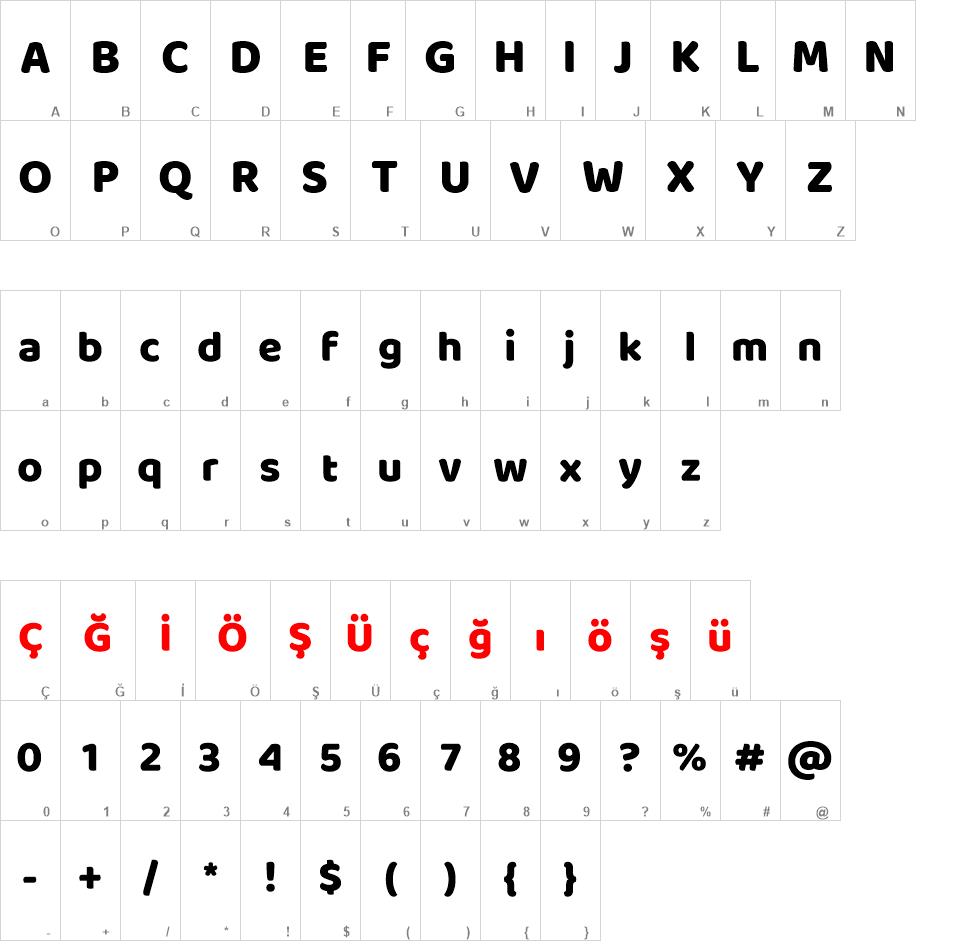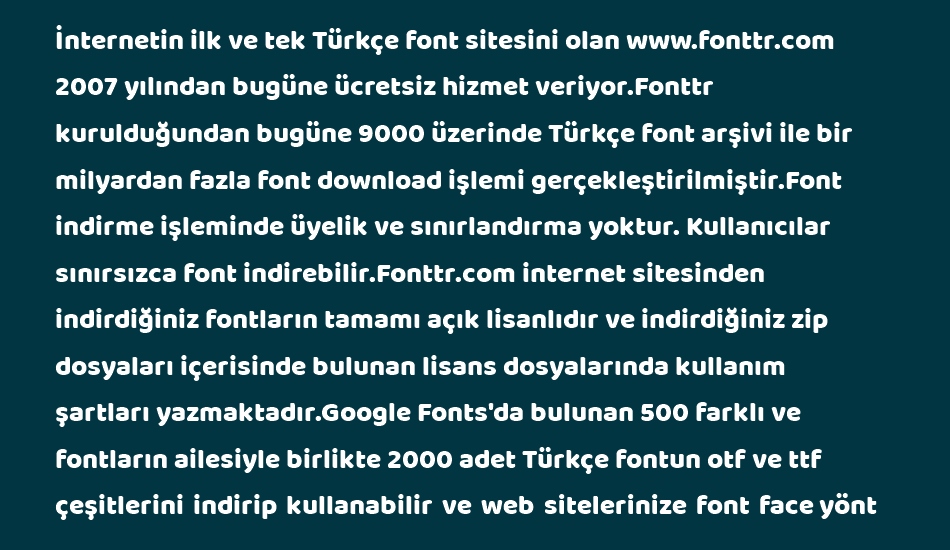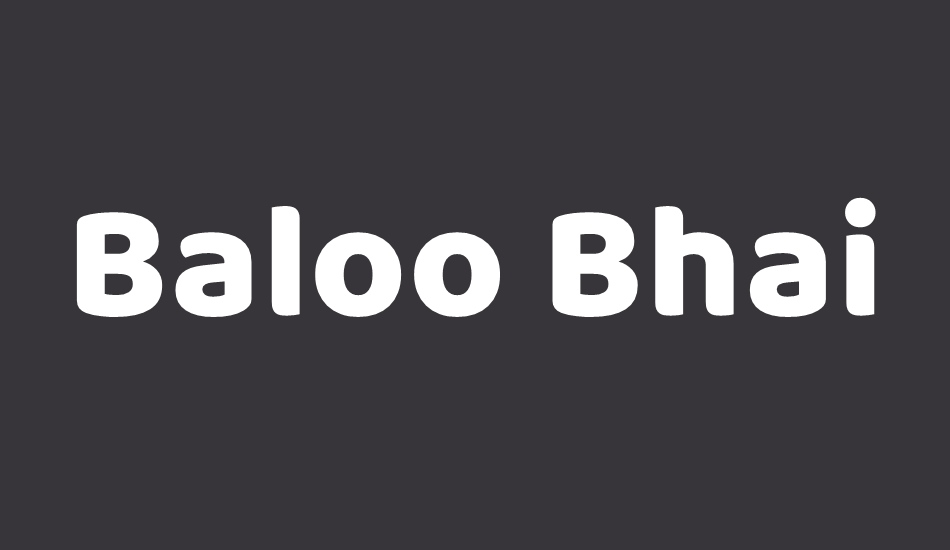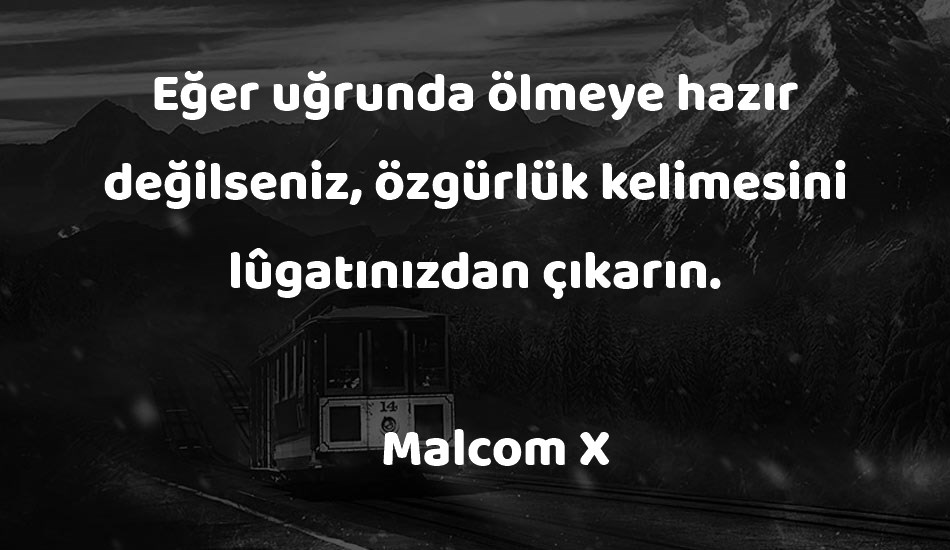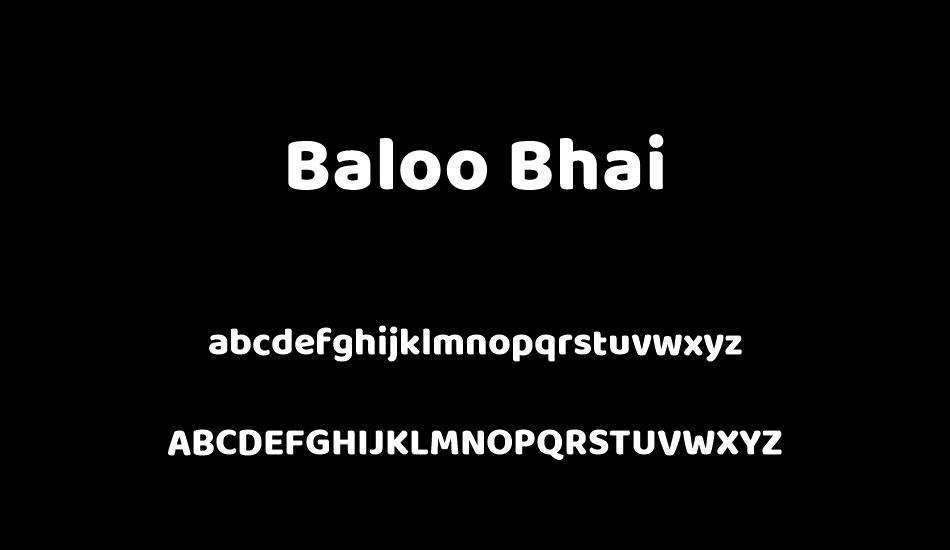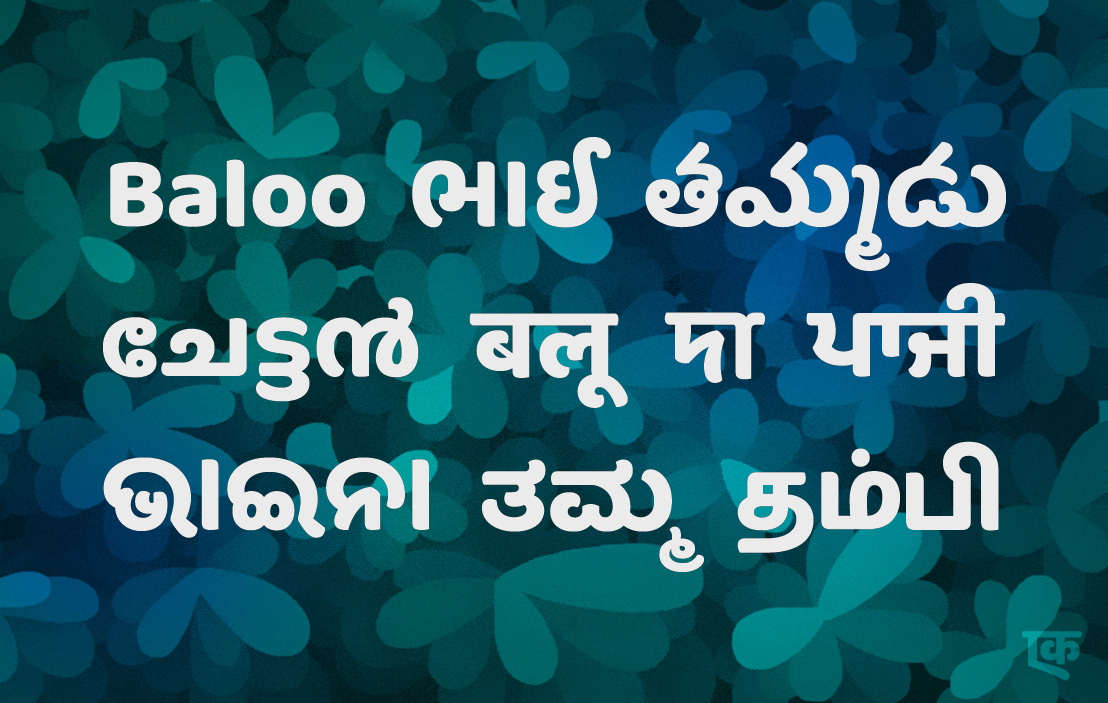
Baloo font
Bir kürk katında sivri pençelerin mükemmel bir karışımı olan Baloo, Ek Type'ın kullanışlı bir ekran yazı biçimidir. Dokuz Hintli senaryonun yanı sıra Latin muadili ile de mevcut olan aileler Unicode'a uyumlu ve libre lisanslıdır.
Baloo, şaşkınlığın ince bir tonuyla ve çıplak ihtiyaçları olan farklı, ağır bir spurless tasarımdır. Tek bir ağırlıkta birkaç betik doldurmak için yazım biçimi, tekli ve çoklu komut dosyalarının kullanımını güvence altına almak için bu nazik ormancılık meselesinin her hareketine eşit adalet vermeye odaklanır. Umutsuz ama kendinden emin, sıcak ancak eğlenceli, cömert ve anlaşılır olan Baloo, her yere giderken her yere can verir.
Baloo font projesi dokuz İndik Komut Dosyası'nın her biri için benzersiz yerel adlarla dokuz ayrı yazı tipi geliştirir. Her yazı tipi, bir Hint alt grubuna artı Latin, Latin Genişletilmiş ve Vietnamca'yı destekler.
İyi yazılmış ve her senaryoya özen gösterilmiş, Baloo'yu arıtmak için kararlı bir tip tasarımcılardan oluşan bir ekip taşıdı ve sevdiğimiz yazı karakteri olarak yükseltti. Baloo Devanagari Sarang Kulkarni tarafından tasarlandı. Baloo Latin, Ek Type tarafından ortak olarak tasarlanmıştır. Girish Dalvi tarafından tasarım yardımı ve yazı tipi mühendisliği yazın.
Baloo Bhai font